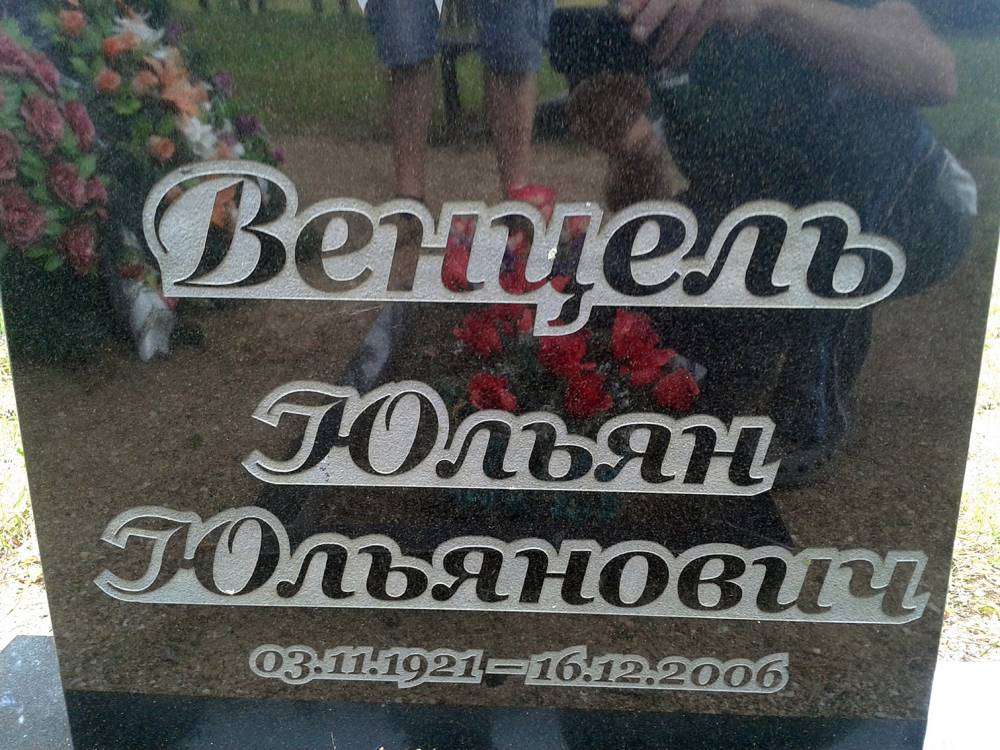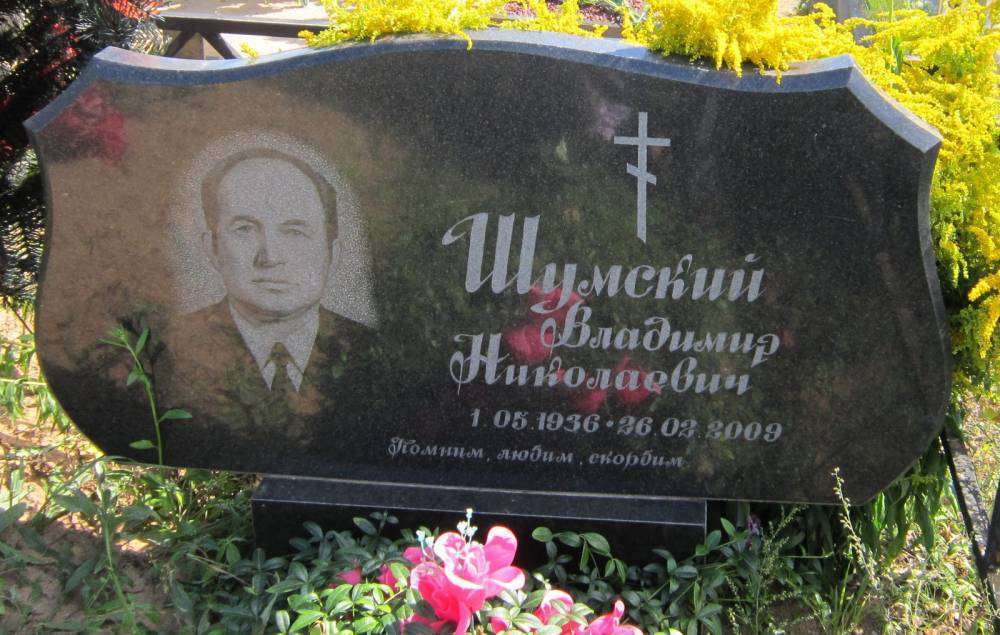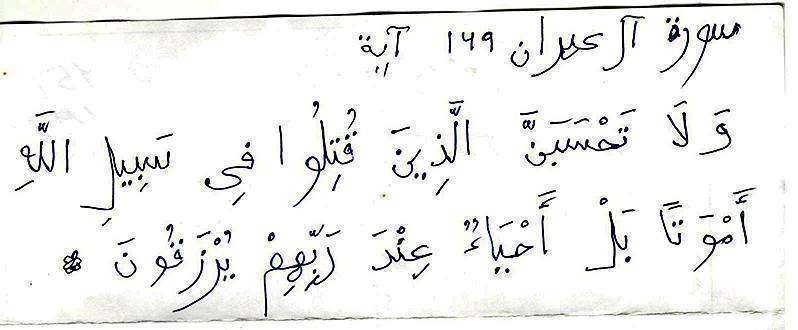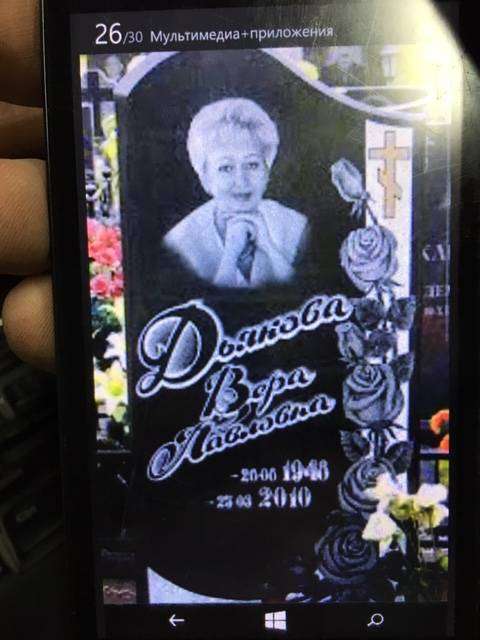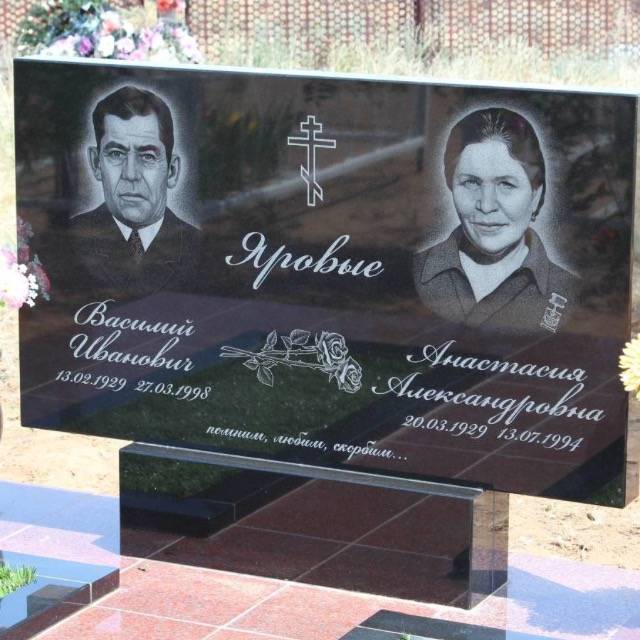
Помогите найти шрифт!
Подскажите пожалуйста название. похожих много, а нужен именно такой. Спасибо!
Ребята, выручите, очень надо такой шрифт... Спасибо
Нашел ИМПАКТ
Подскажите пожалуйста название. похожих много, а нужен именно такой. Спасибо!
Может есть у кого. уже глаза сломал. в поисках
по моему Times New Roman курсив
Нет, не таймс. Газета какая то не помню точного названия. Уже нашел ,фрезеранул и золотом вскрыли.
Вот этот.
Gazeta Titul Bold Italic
В инете можно найти по фото.Я тоже так нашла . мне никто не помог,к сожалению
Помогите определить шрифт или похожий шрифт.
В инете можно найти по фото.Я тоже так нашла . мне никто не помог,к сожалению
что это за шрифт?
Заглавные "Boyarsky"  ,
Остальные "Georgia" жирный курсив
Ребята подскажите что за чудо шрифт
Я не гравер , я художник , а шрифты на сайтах нахожу или сама в фотошопе рисую подходящий.
Подскажите шрифт, пожалуйста:
то, что вручную писали - вижу,
но вроде что-то очень знакомое.
Форумчане привет..у кого арабская клава ,помогите написать по печатному шрифту.